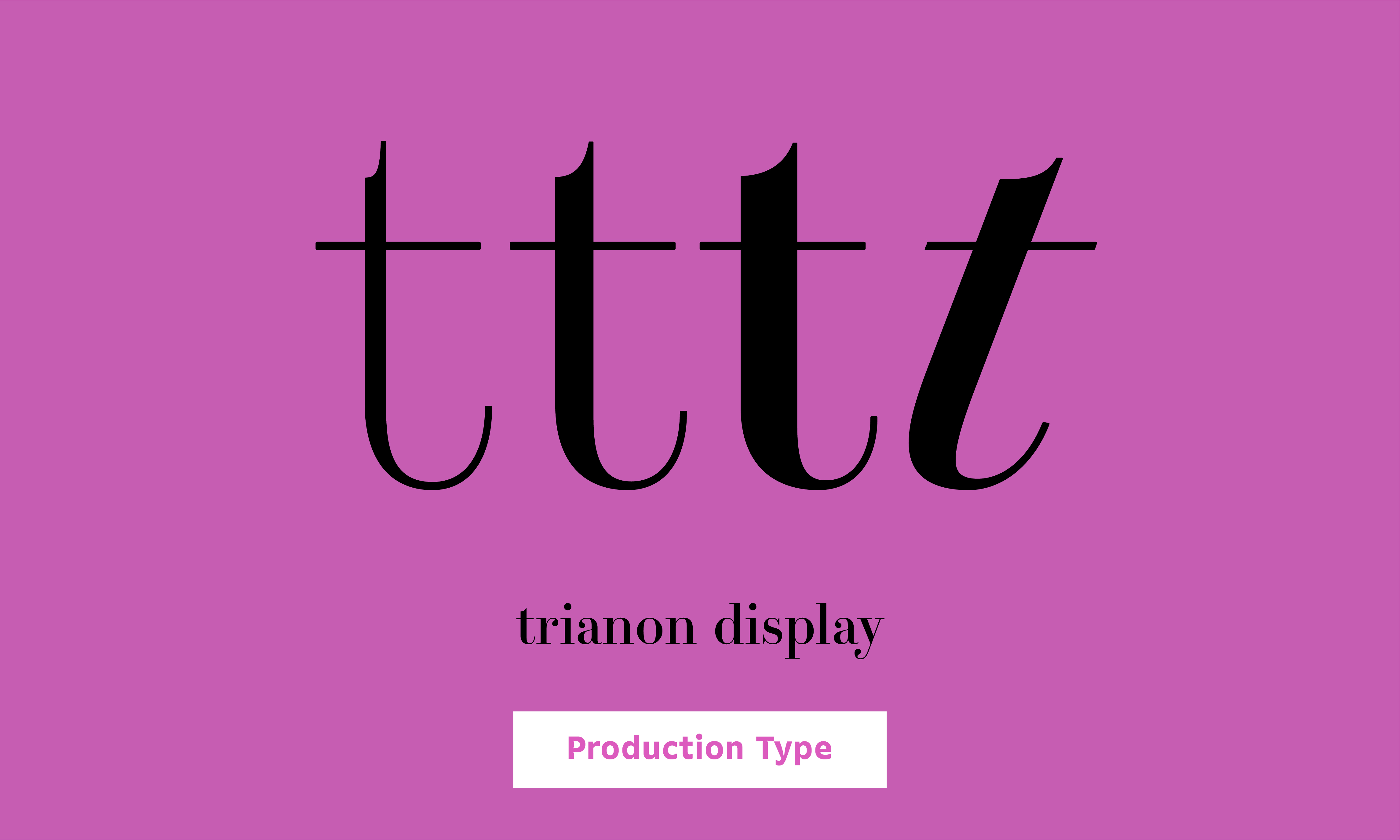
Trianon Display
Trianon은 패션잡지나 명품브랜드에서 자주 사용하는 Didot과 유사하지만 화려한 장식보다는 리듬과 가독성 등에 보다 집중한 폰트이다.
Trinon Display와 Grande는 특히 기존의 Didot과 유사하게 화려한 장식과 명백히 대조적인 인상으로 디자인 되었다.
- Loïc Sander Roxane Gataud Sandra Carrera Yoann Minet